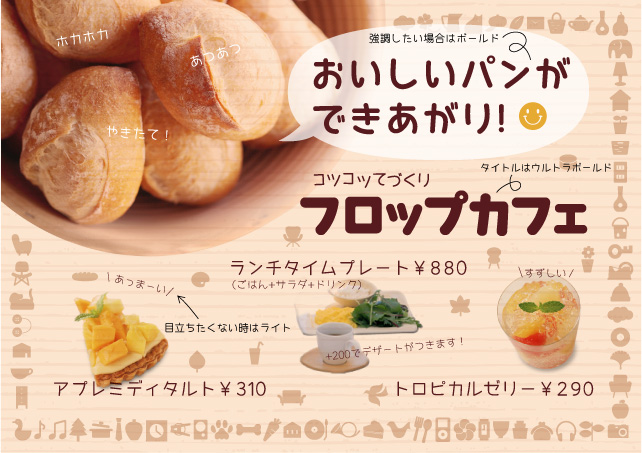
手書き風日本語フォントAiko(アイコ)フォントとは Aikoは20代前後の女性の手書き文字を参考にして作成した書体です。近年の女性の文字のクセを取り入れつつもデザインとして統一感のある書体です。しっかりとした考え方を持ちつつも、女性らしい可愛らしさをもっている。そんな女性像をイメージした書体です。ひらがな、カタカナ、アルファベット、記号のみの書体ですが、一般的な丸ゴシックの漢字と組み合わせて使える、最適な線の太さになっています。手書きを手本にしている為、漢字に対してカナが小さいデザインになっており、文章、見出しともに読みやすくなっています。  |